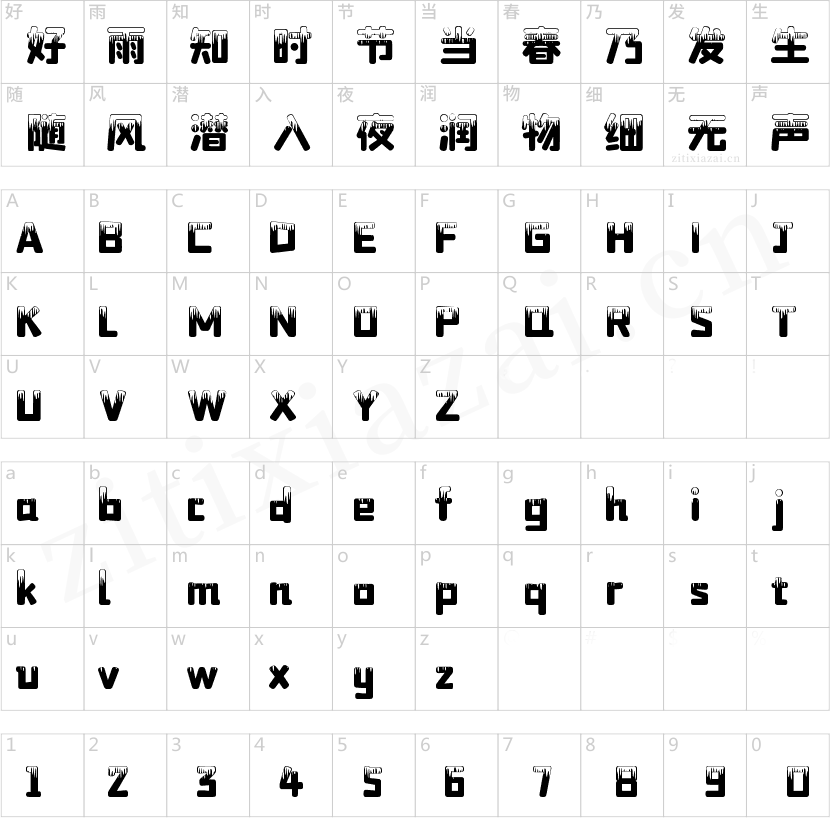
字魂191号-奶油雪糕体,字小魂奶油雪糕体
字魂191号-奶油雪糕体,字小魂奶油雪糕体,这款字体结构工整、笔画清晰,兼顾美观与易读性,适用于标题、正文、海报、包装、LOGO 等多种场景。字形优雅稳定,风格百搭耐看,适配日常排版与创意设计,让文字呈现更舒适、更具质感。字魂191号-奶油雪糕体,字小魂奶油雪糕体一笔一画,皆是细节,以均衡的比例、流畅的线条打造舒适视觉体验,字形端正大气,风格简约现代。无论是商业设计、品牌宣传还是日常排版,都能轻松驾驭,让文字更有格调与力量。字魂191号-奶油雪糕体,字小魂奶油雪糕体字体下载。
字魂字体字小魂奶油雪糕体字体是由字魂创意字库设计并生产的一款可商用的字体,被收录于字小魂系列。该字体支持GB-2312标准,包含6763个中文、字母、符号和数字,字体类型偏向创意字体,具有可爱、圆润的风格,在市面上广泛用于媒体&H5、旅游、标题等场景。